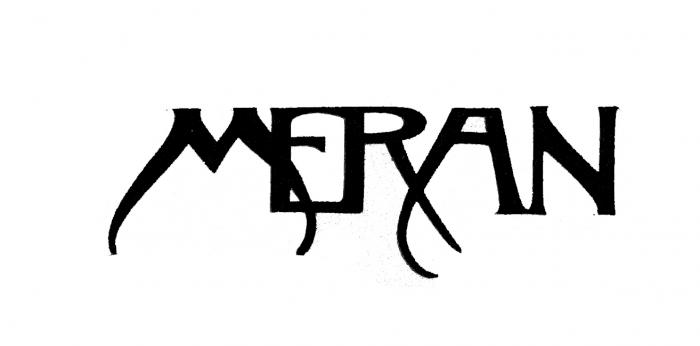
Historische Schrift von 1889
brauche eure Hilfe. Suche eine ganz bestimmte Schrift von 1889. Wahrscheinlich werde ich sie nicht finden aber vielleicht kennt jemand eine ähnliche??? Die dieser historischen Schrift gleicht?
Wäre sehr froh wenn mir jemand helfen könnte sonst muss ich die anderen Buchstaben selbst erfinden ; )
Ich fürchte jedenfalls auch, dass du dann wohl die anderen Buchstaben selbst erfinden, und die vorhandenen zu Einzelbuchstaben noch korrigieren musst, denn das sieht doch sehr wie genau so direkt gezeichnet aus.
Ich habe es erst für irgendwas jugendstiliges von Archibald Knox gehalten, aber zu wenige echte Übereinstimmungen gefunden. Es gibt einen Archibald Font, mit dem du aber wohl nicht glücklich wirst:
Tatsächlich findest du jedoch viele Grundformen deiner Schriftprobe in Tobacco Road NF Font wieder:
Damit hättest du wenigstens einen passenden Zeichenvorrat. Die Proportionen von E und N sehen gut aus. Mir kommt das nicht wie ein Zufall vor. Das R wurde schlicht verlängert. M und A sind wohl Neuschöpfungen.
Das Buch heißt: "Kurort Meran. Den Festgästen der 77. Versammlung Deutscher Naturforscher und Ärzte gewidmet." Wie gesagt von 1889.
Danke für die Tobacco Schriftart. Kann ich wirklich gut gebrauchen als Zeichengrundform. Der Rest wird dazu erfunden ; )
Dann freut es mich, dass ich etwas helfen konnte. Das wirkliche Erscheinungsjahr passt besser zu meiner Einschätzung: